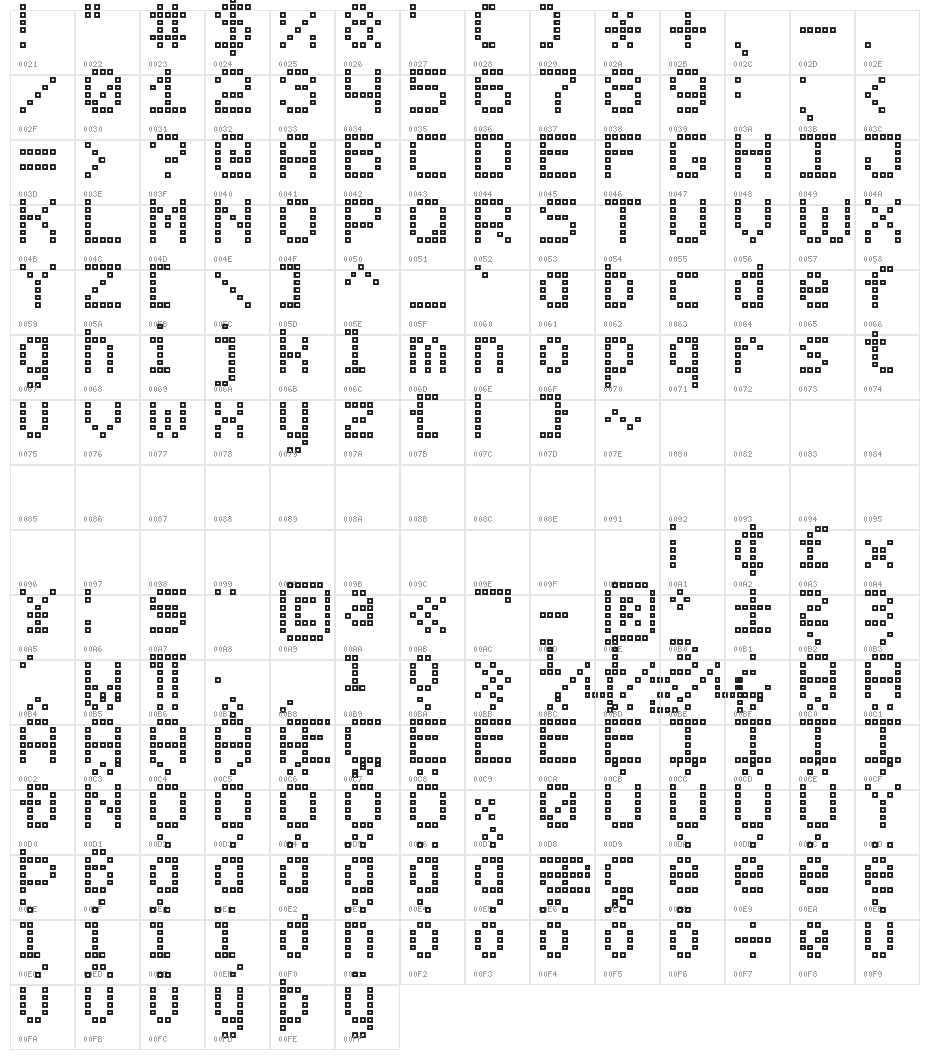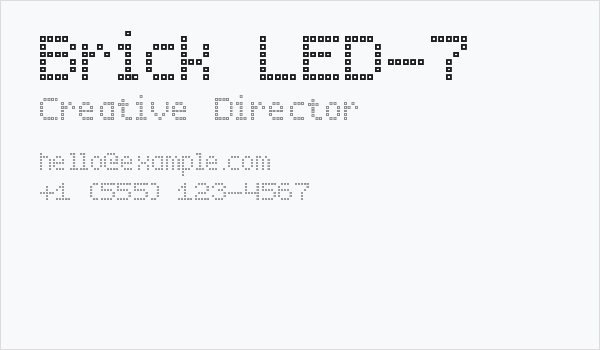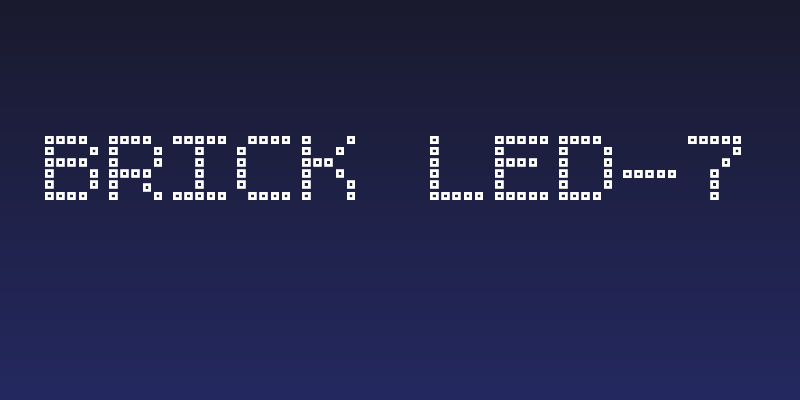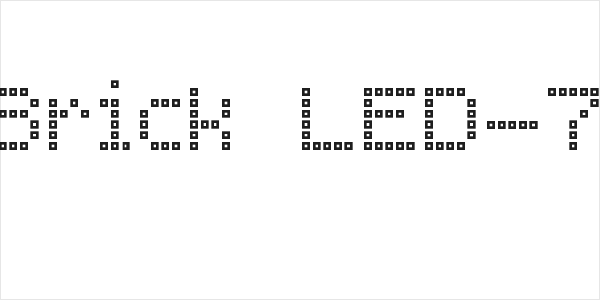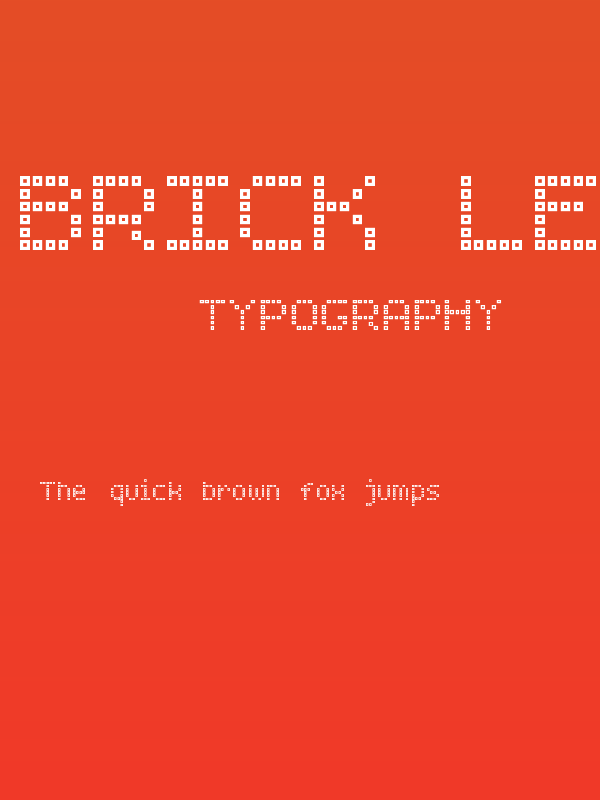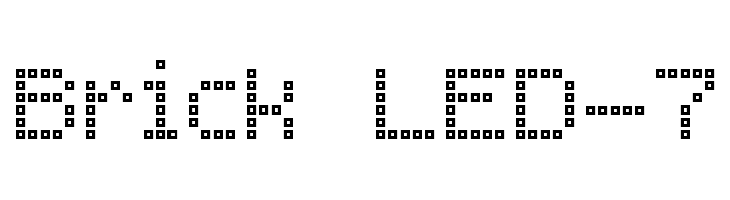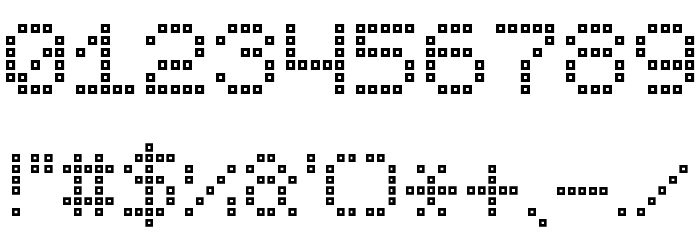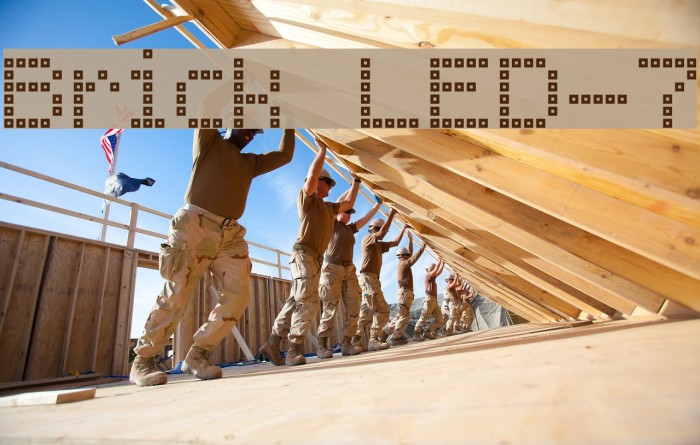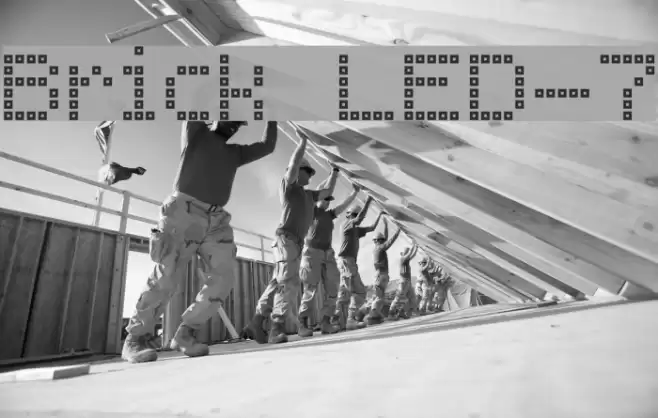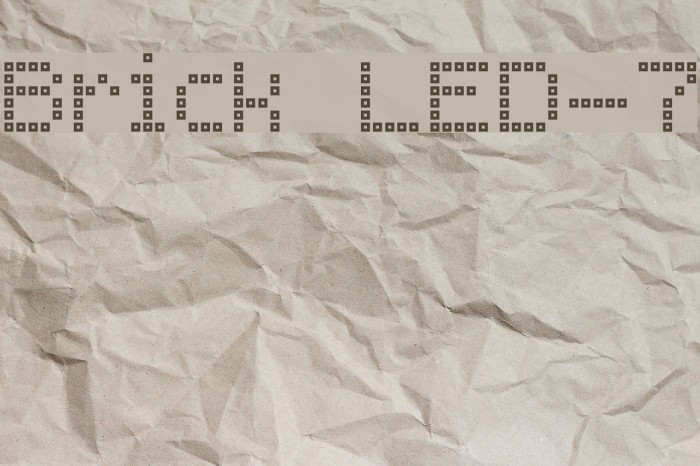
Brick LED-7 Font
✎ Futuristic
| Vorgeschlagene Projekte | Ideal for digital displays, tech-themed designs, retro video games, and futuristic branding. |